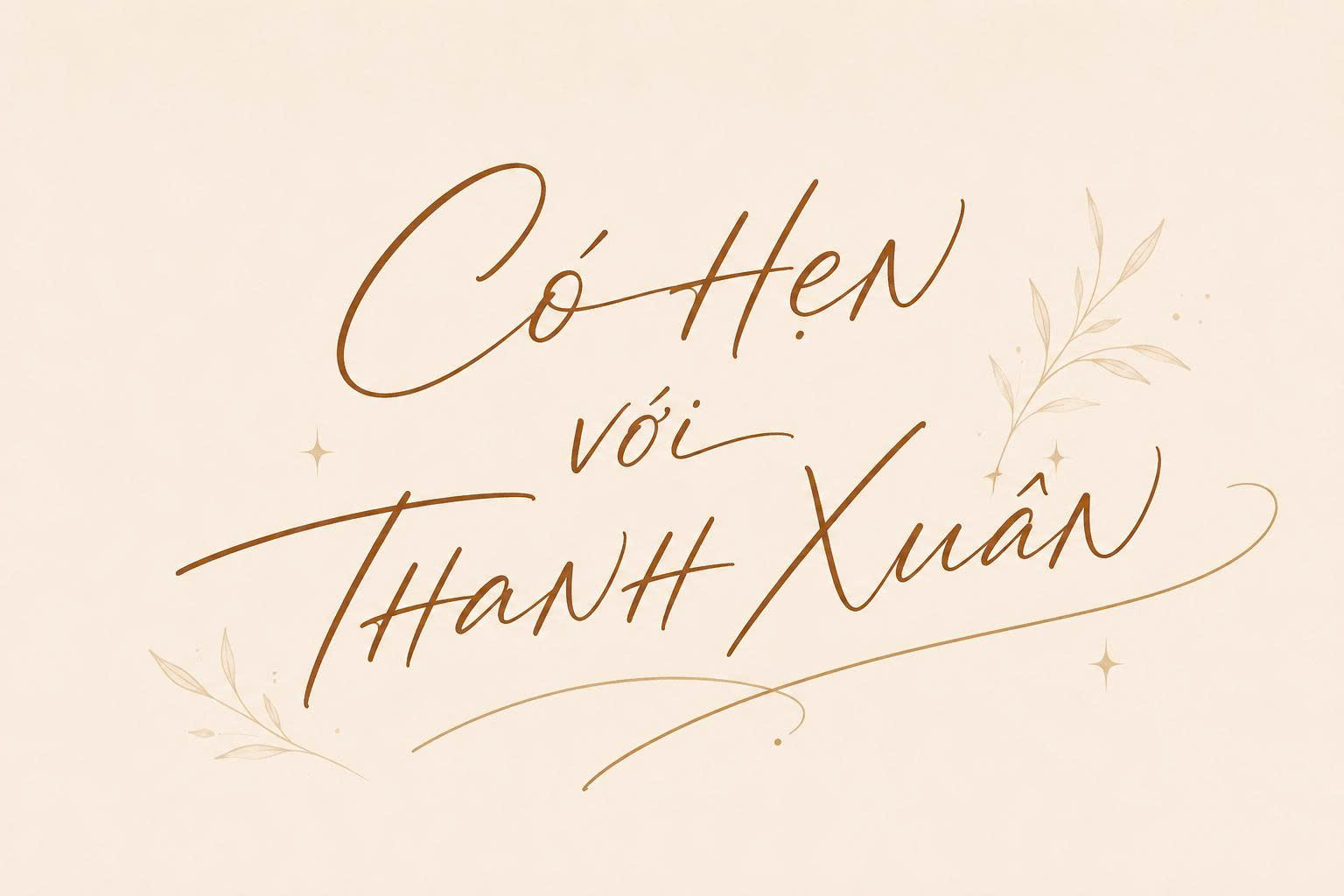
Font chữ ký Việt hóa là bộ sưu tập các phông chữ mô phỏng chính xác nét viết tay tự nhiên của con người với những đường uốn lượn, thanh đậm và độ kết nối đặc trưng như một chữ ký thật. Việc sử dụng font chữ ký giúp các bản thiết kế trở nên cá tính, gần gũi và mang đậm tính độc bản, đặc biệt là trong các ấn phẩm cao cấp. Doozypack.vn chia sẻ link download font chữ ký việt hóa chuẩn, giúp bạn giải quyết triệt để lỗi nhảy dấu tiếng Việt để tự tin thiết kế bao bì, logo hay các thiệp mời sang trọng.
Tại sao nên sử dụng font chữ ký đẹp Việt hóa trong thiết kế?
Sử dụng phông chữ ký không chỉ đơn thuần là trình bày nội dung, mà là cách thương hiệu gửi gắm tâm huyết và sự chân thành đến khách hàng.
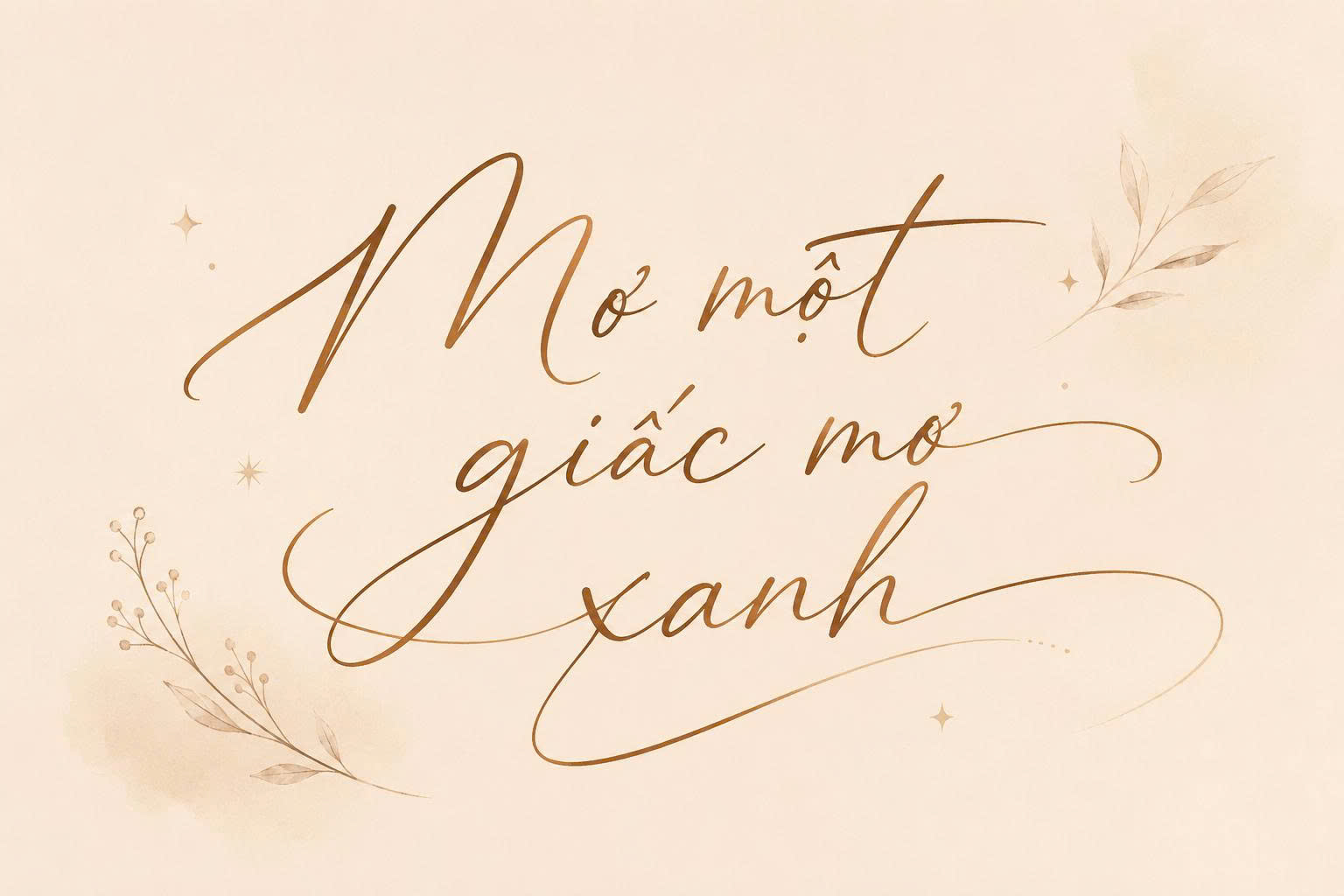
Tạo dấu ấn cá nhân hóa và sự độc bản
Mỗi font chữ ký đẹp Việt hóa mang một sắc thái riêng: từ sự mạnh mẽ, quyết đoán đến nét mềm mại, bay bổng. Trong thiết kế thương hiệu cá nhân hoặc bao bì sản phẩm handmade, một dòng chữ ký viết tay giúp tạo niềm tin cho người tiêu dùng, khẳng định chất lượng và sự cam kết của người đứng đầu thương hiệu.
Tăng tính thẩm mỹ và sự sang trọng cho thương hiệu
Các dòng font chữ ký viết tay Việt hóa thường có các nét nối (ligatures) và nét uốn (swashes) rất tinh tế. Khi được sắp đặt hợp lý trên nắp hộp giấy, túi giấy Ivory cán mờ hoặc thiệp chúc mừng, chúng tạo nên một vẻ đẹp tối giản nhưng vô cùng đẳng cấp, thường thấy ở các nhãn hàng thời trang và mỹ phẩm cao cấp.
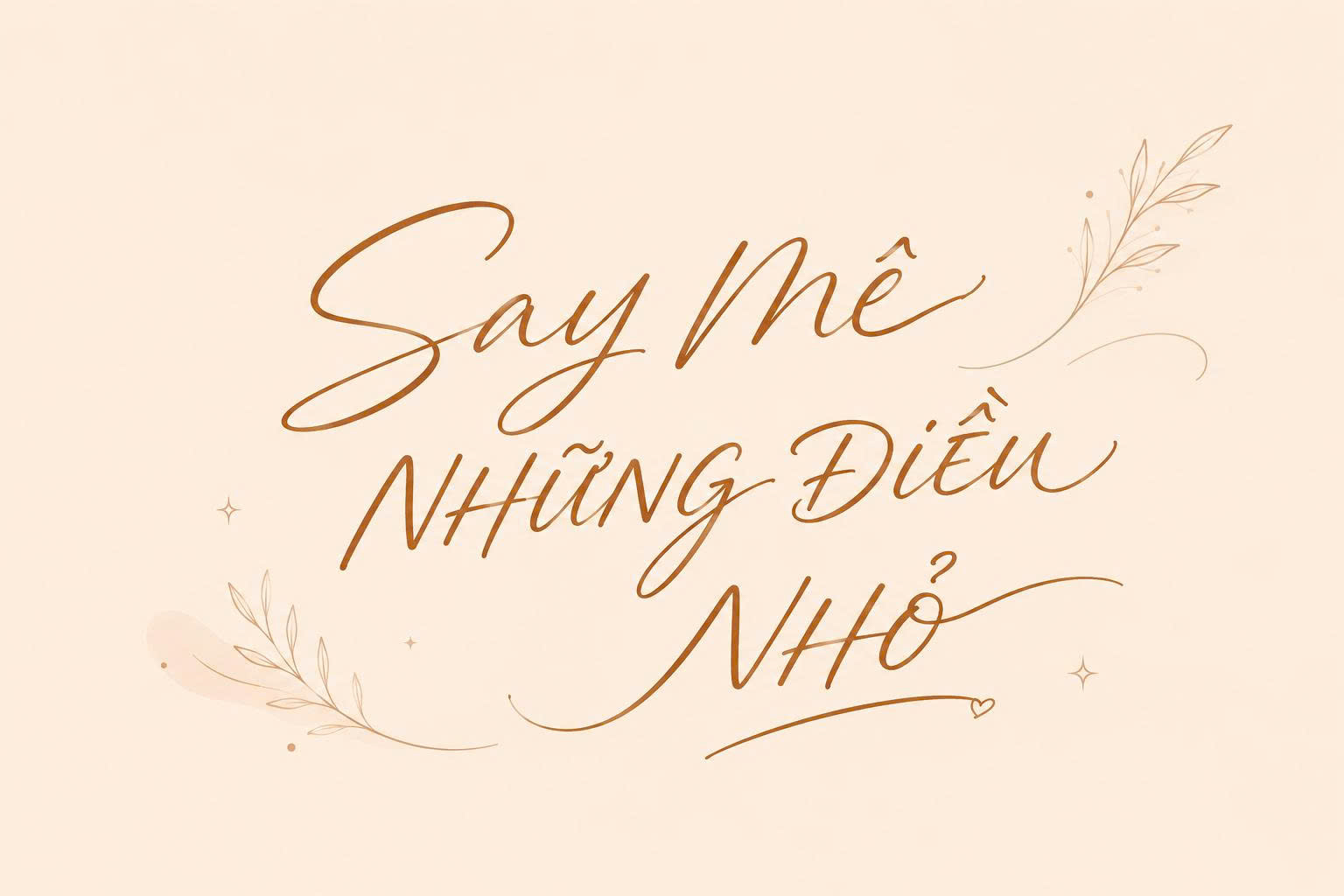
03 Ứng dụng của font chữ ký viết tay Việt hóa trong sản xuất bao bì
Tại xưởng in của Doozypack.vn, font chữ ký là một trong những lựa chọn hàng đầu để tạo điểm nhấn cho các sản phẩm:
- Thiệp cảm ơn (Thank you card): Một dòng chữ ký cuối thư cảm ơn giúp khách hàng cảm thấy được trân trọng, từ đó gia tăng sự gắn kết với thương hiệu.
- Hộp giấy quà tặng: In tên người nhận hoặc người gửi bằng font chữ ký trên hộp quà giúp món quà trở nên ý nghĩa và mang tính riêng tư cao hơn.
- Tem nhãn nhũ vàng: Font chữ ký khi kết hợp với kỹ thuật in nhũ trên tem nhãn mỹ phẩm, chai vang tạo nên diện mạo vô cùng chuyên nghiệp và đắt tiền.
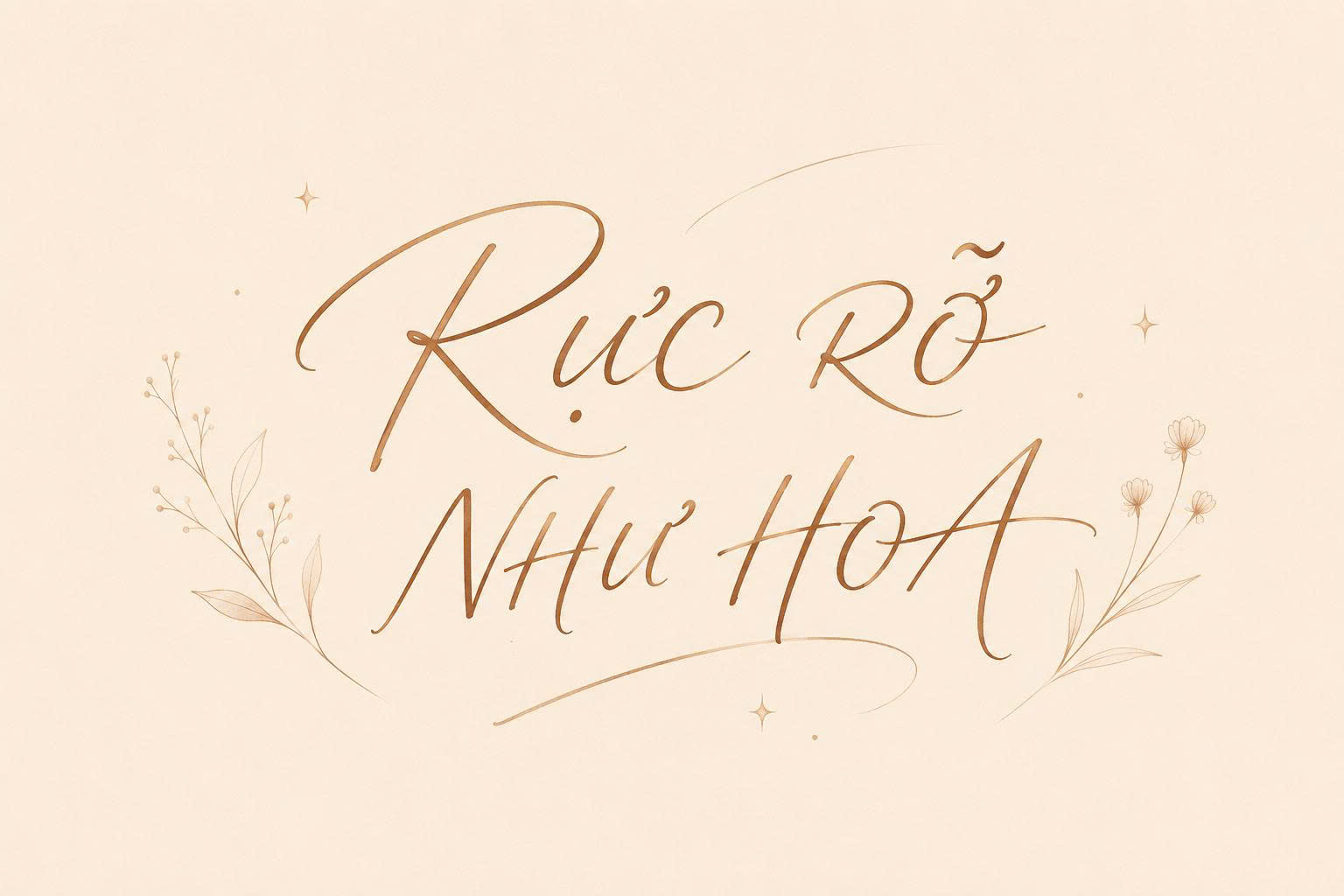
03 Lưu ý kỹ thuật quan trọng khi in ấn font chữ ký nét mảnh
Việc đưa một font chữ có nét mảnh như tóc (hairline) lên chất liệu giấy đòi hỏi sự am hiểu kỹ thuật sản xuất của Doozypack.vn:
- Vấn đề ép kim (Hot Stamping): Font chữ ký thường có những nét vuốt rất nhẹ. Nếu bạn muốn ép kim vàng hoặc bạc, hãy đảm bảo nét chữ có độ dày tối thiểu 0.15mm để nhũ có thể bám đều, tránh bị bong tróc hoặc mất nét.
- Lưu ý về độ sắc nét: Luôn sử dụng font chữ định dạng vector. Tuyệt đối không dùng ảnh chữ ký dạng PNG/JPG để in ấn trên bao bì lớn vì sẽ gây hiện tượng vỡ nét, nhòe màu.